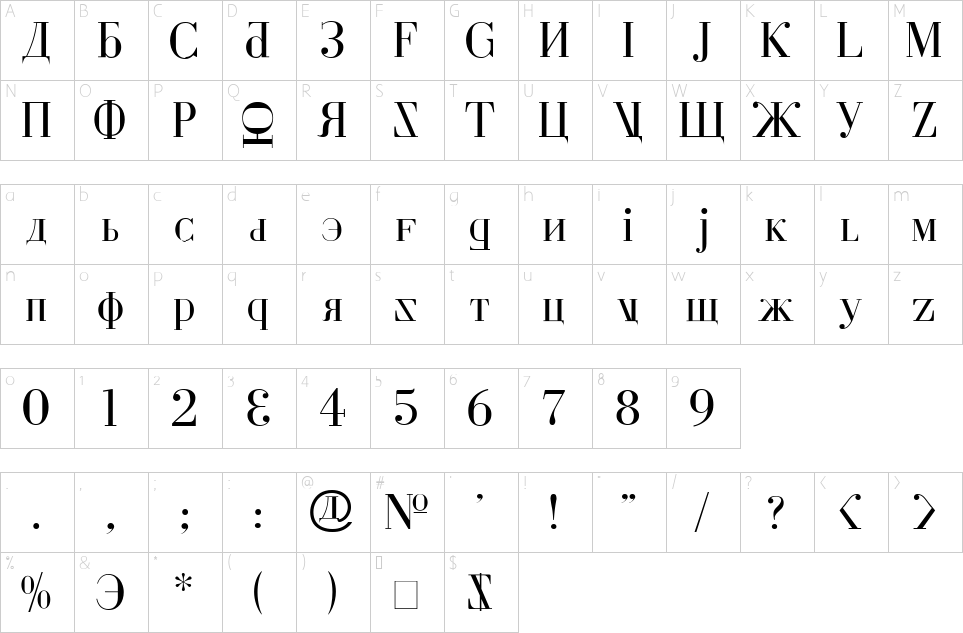
A Cyberia é uma fonte gráfica original, projetada por Iconian Fonts, que oferece um toque de criatividade e modernidade para seus trabalhos. Se você está procurando uma fonte que dê um toque especial a seus designs digitais, a Cyberia é uma escolha ótima. Esta fonte, disponível tanto para Windows quanto para Mac, tem sido descarregada mais de 89,306 vezes, demonstrando seu valor como opção de fonte para designers digitais e aspirantes. A Cyberia traz consigo um toque de sofisticação e criatividade, sem perder o clima alegre e alegre que caracteriza a sua temática. Seja para criar sites web, e-books, logotipos ou qualquer outra forma de design digital, a Cyberia é uma escolha inteligente. Descarregue a fonte gratuitamente e experimente-a agora.